El glifo como emisor de partículas. El contorno de cada letra actúa como fuente de emisión en X-Particles — las partículas brotan, se fusionan y forman una masa orgánica de apariencia biológica que conserva, en su volumen, la memoria de la forma tipográfica original.
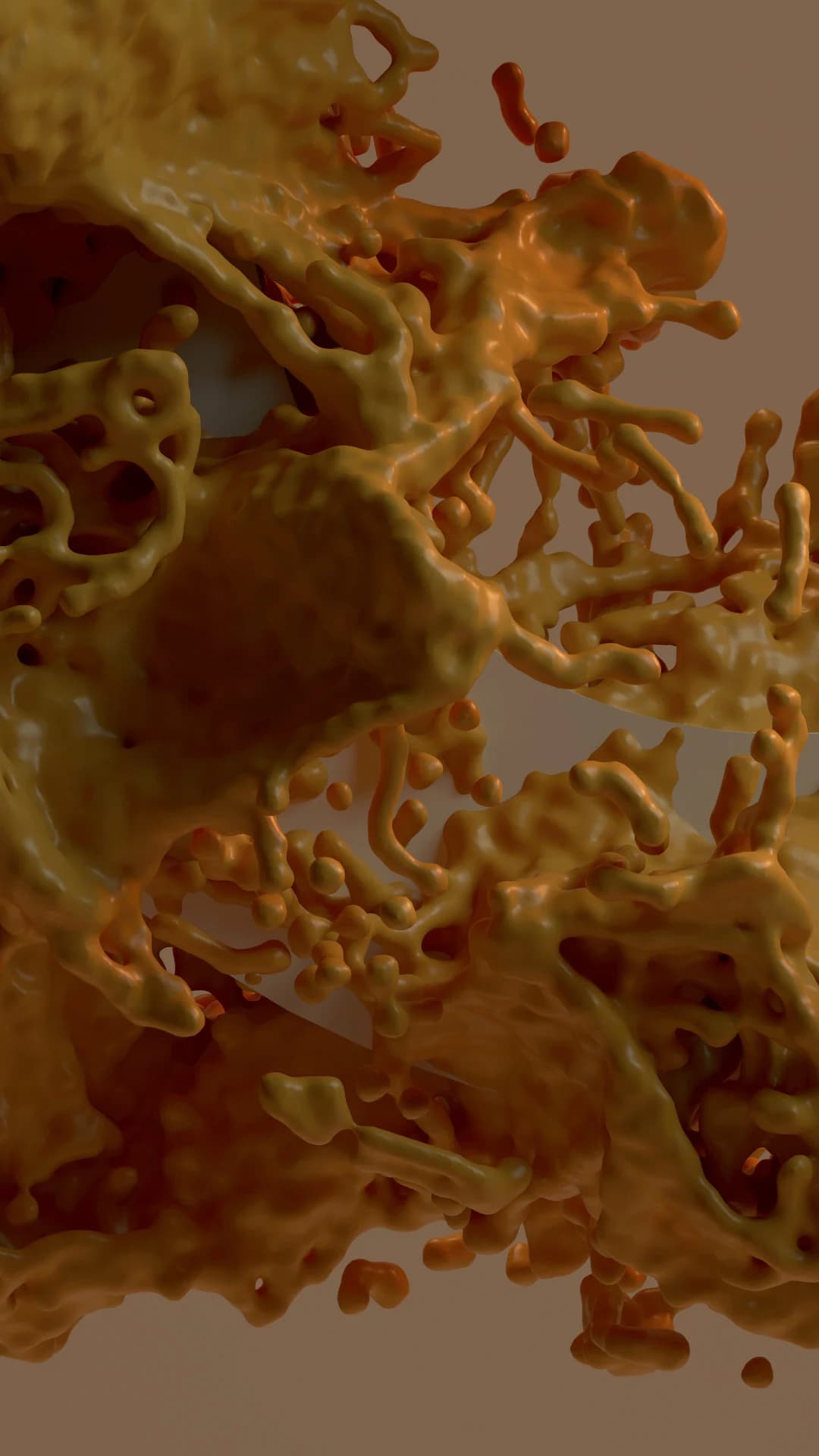
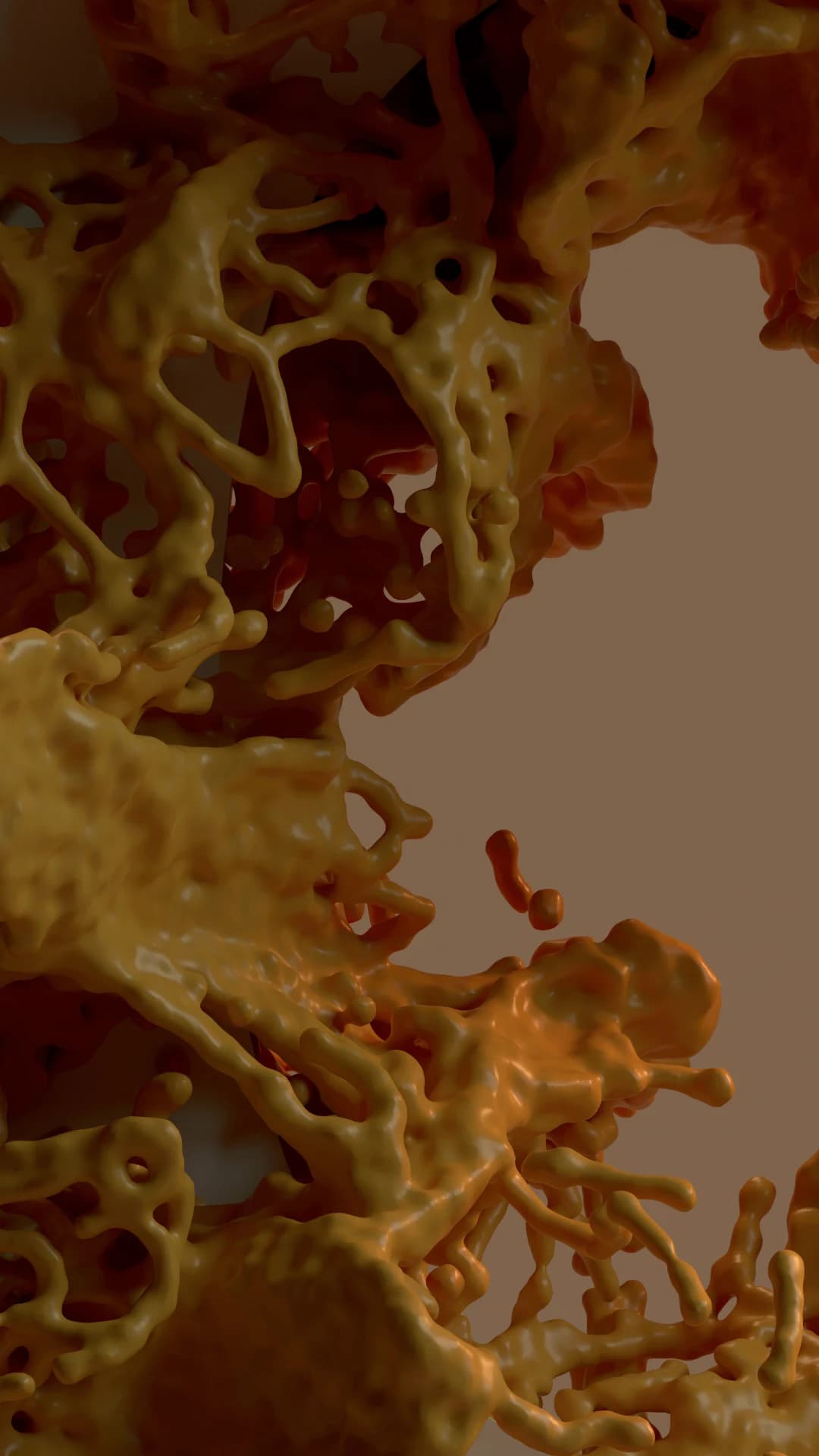
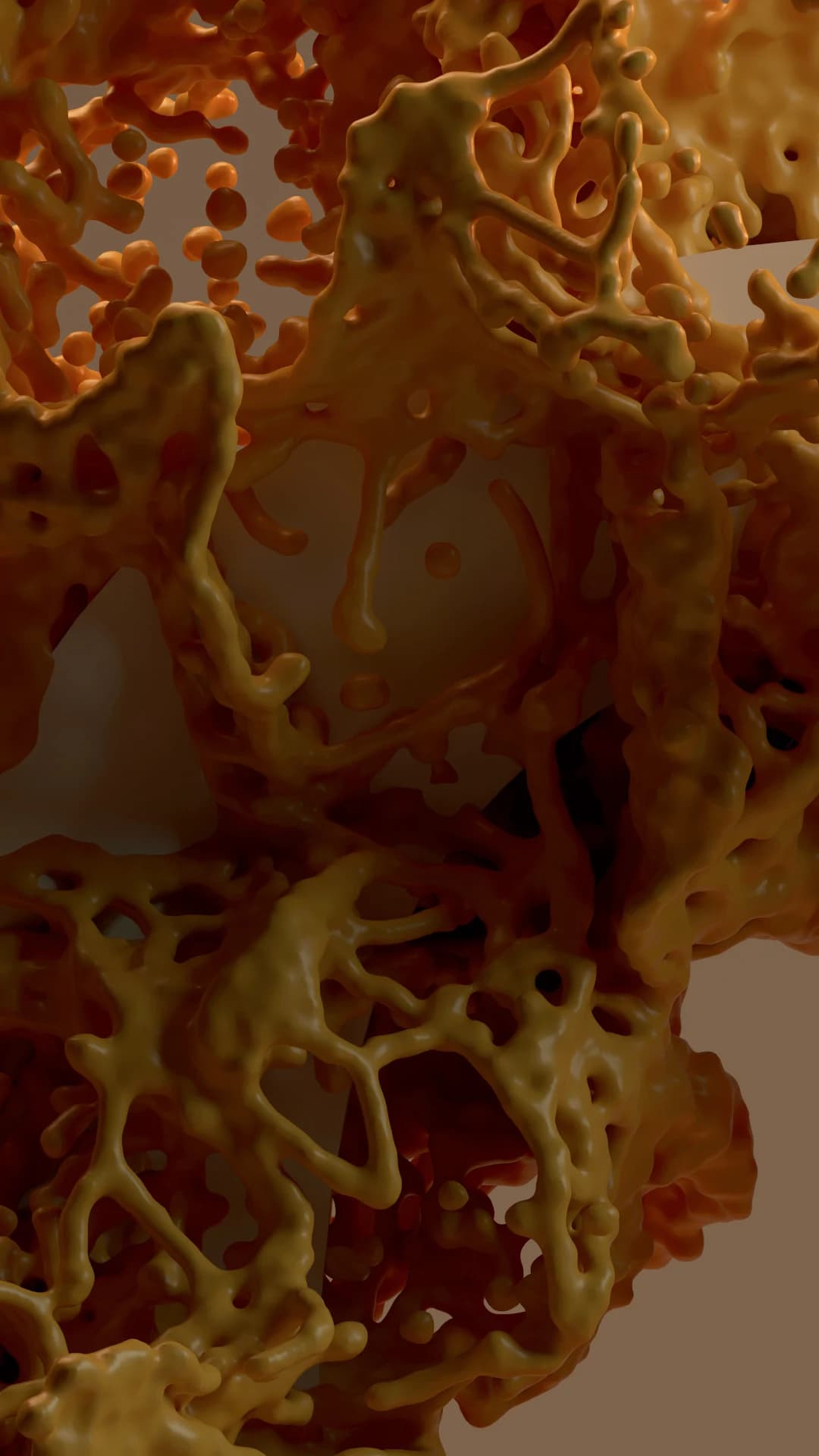
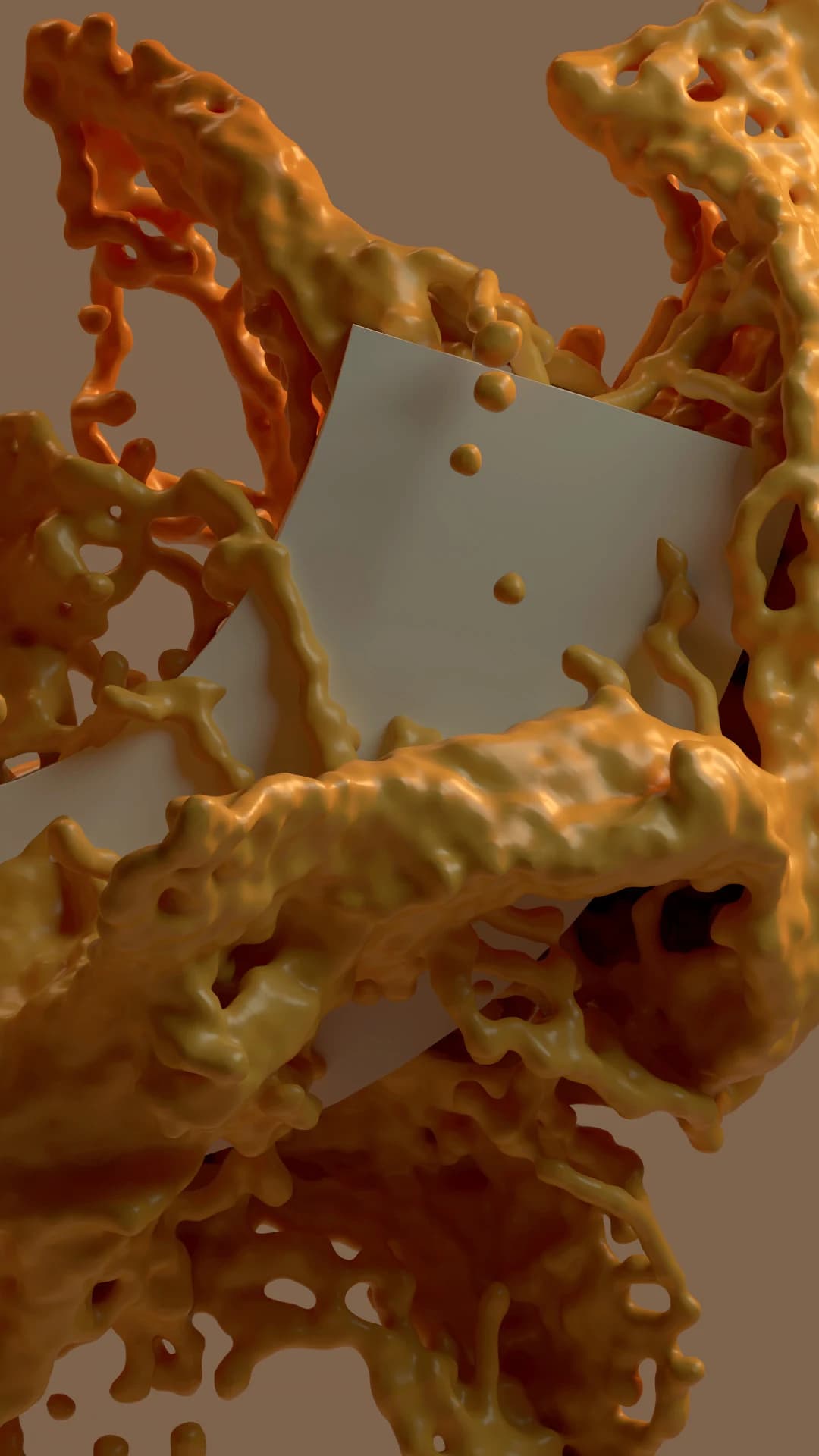
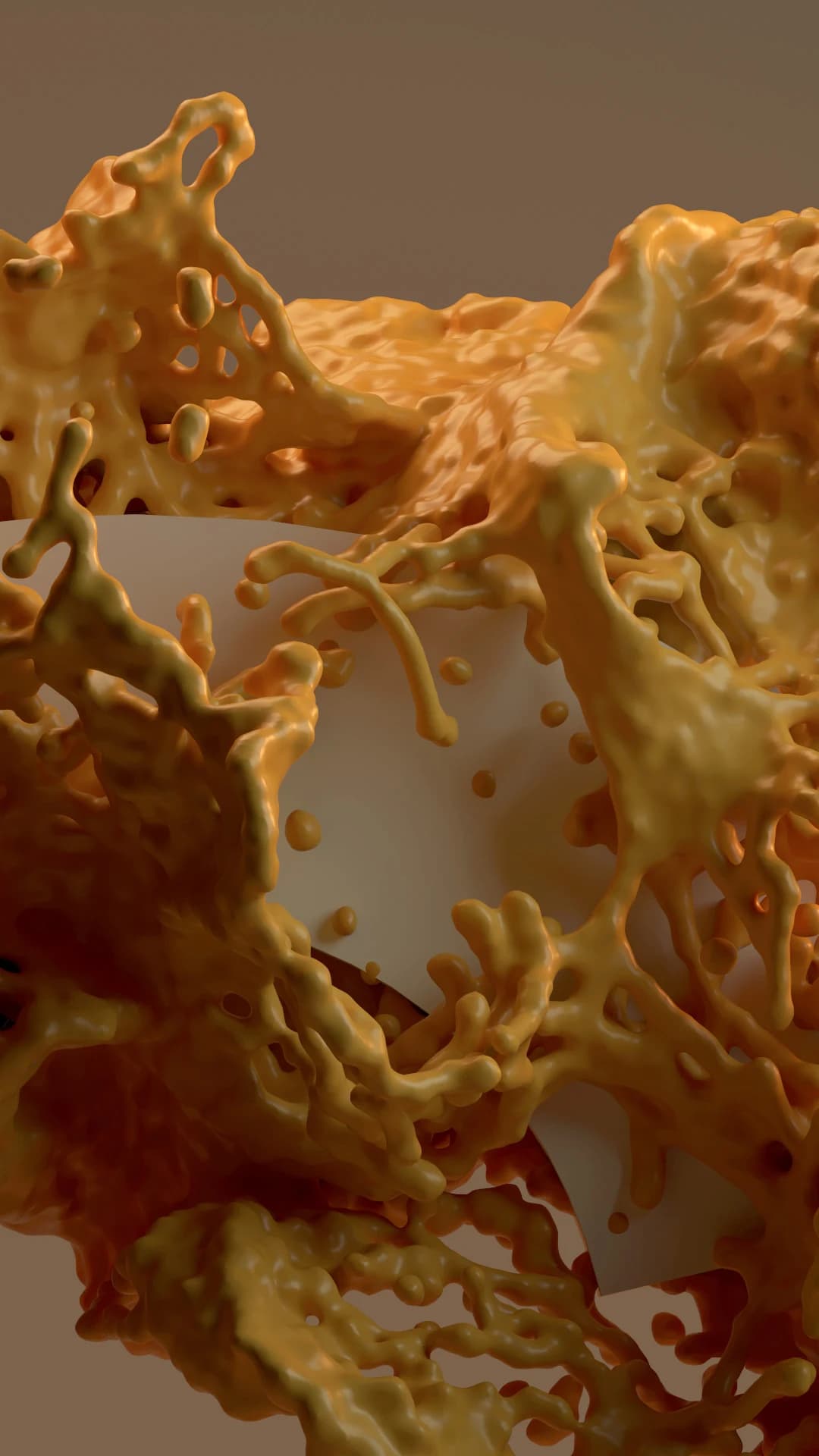
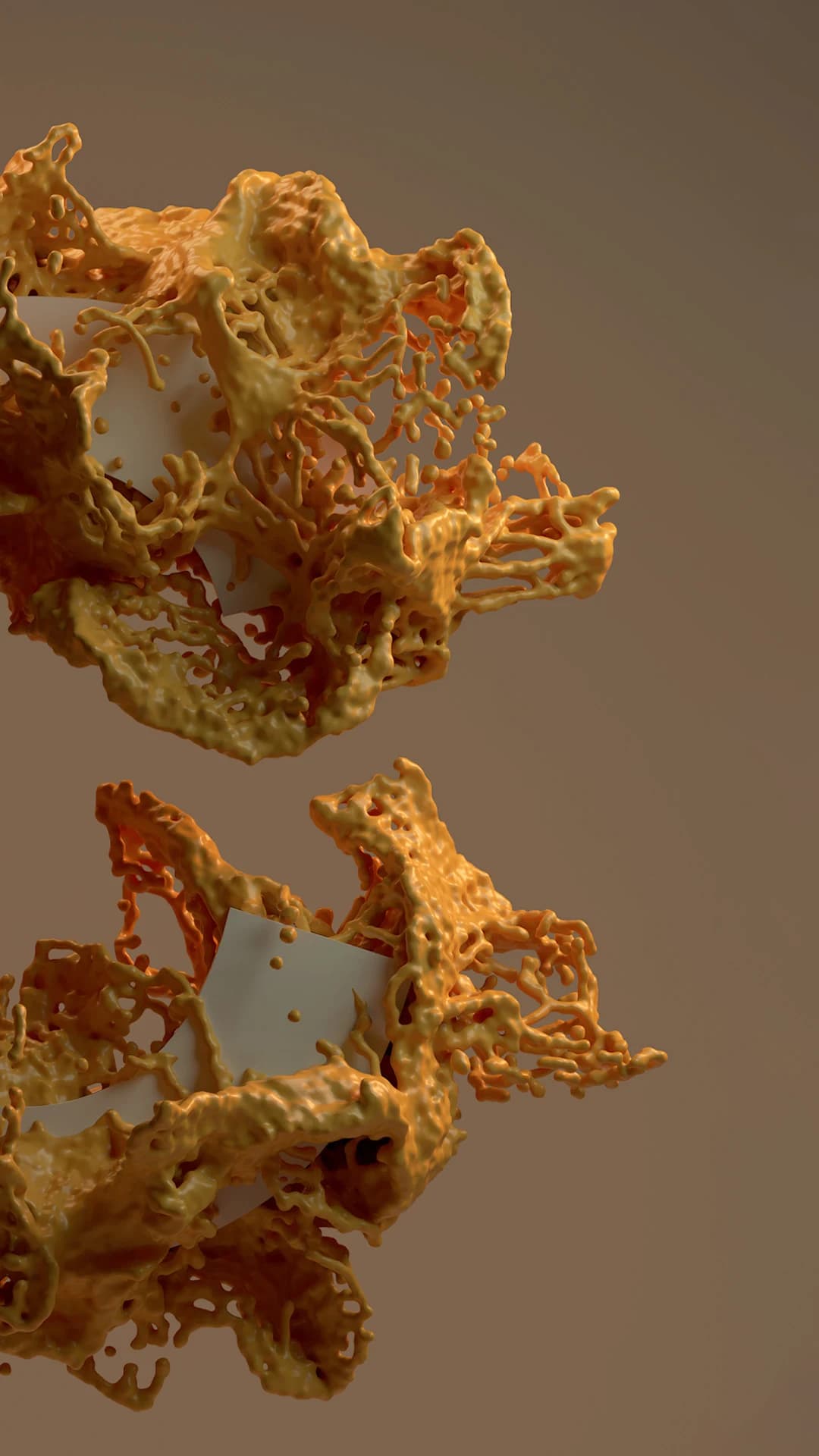
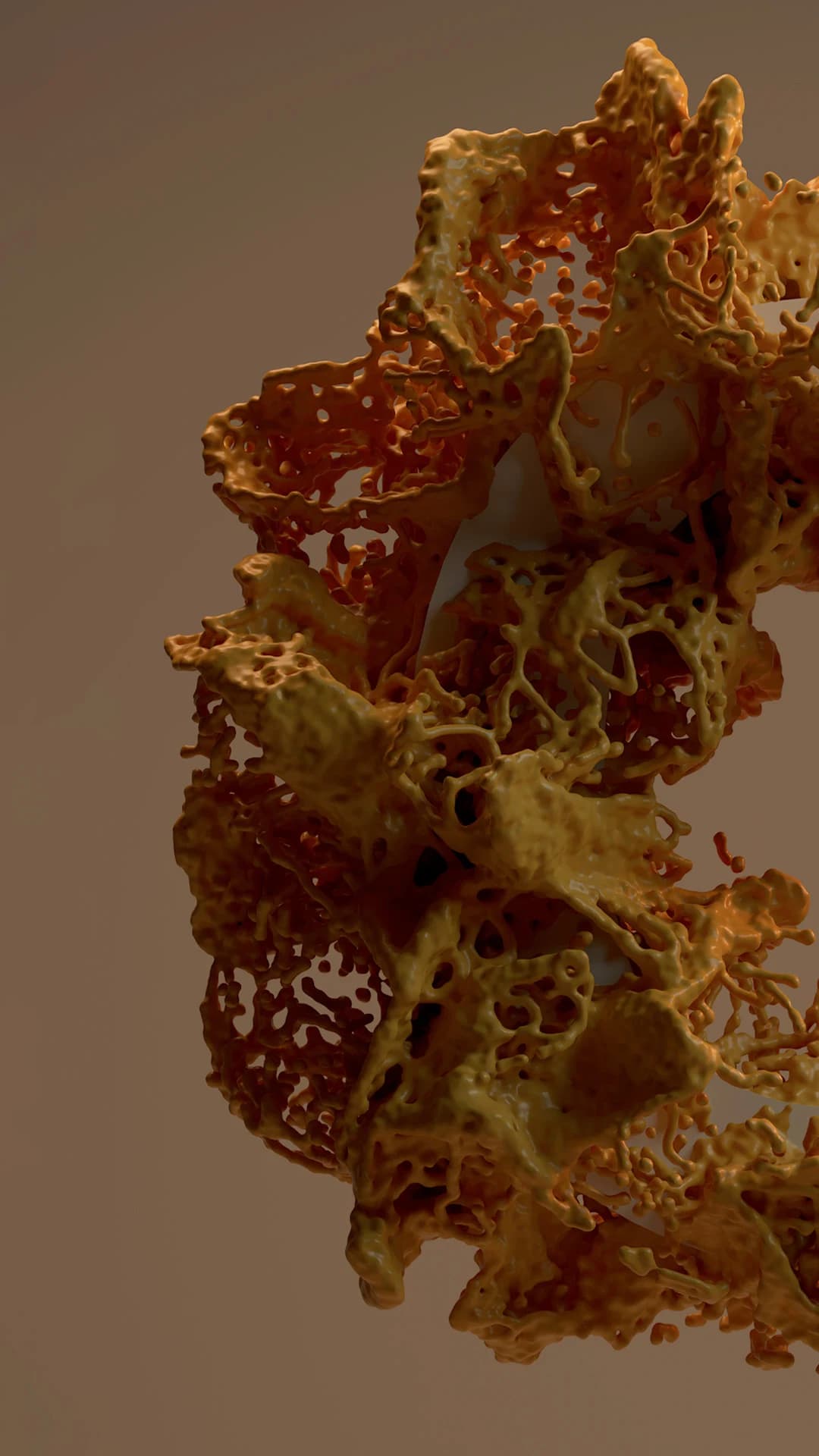
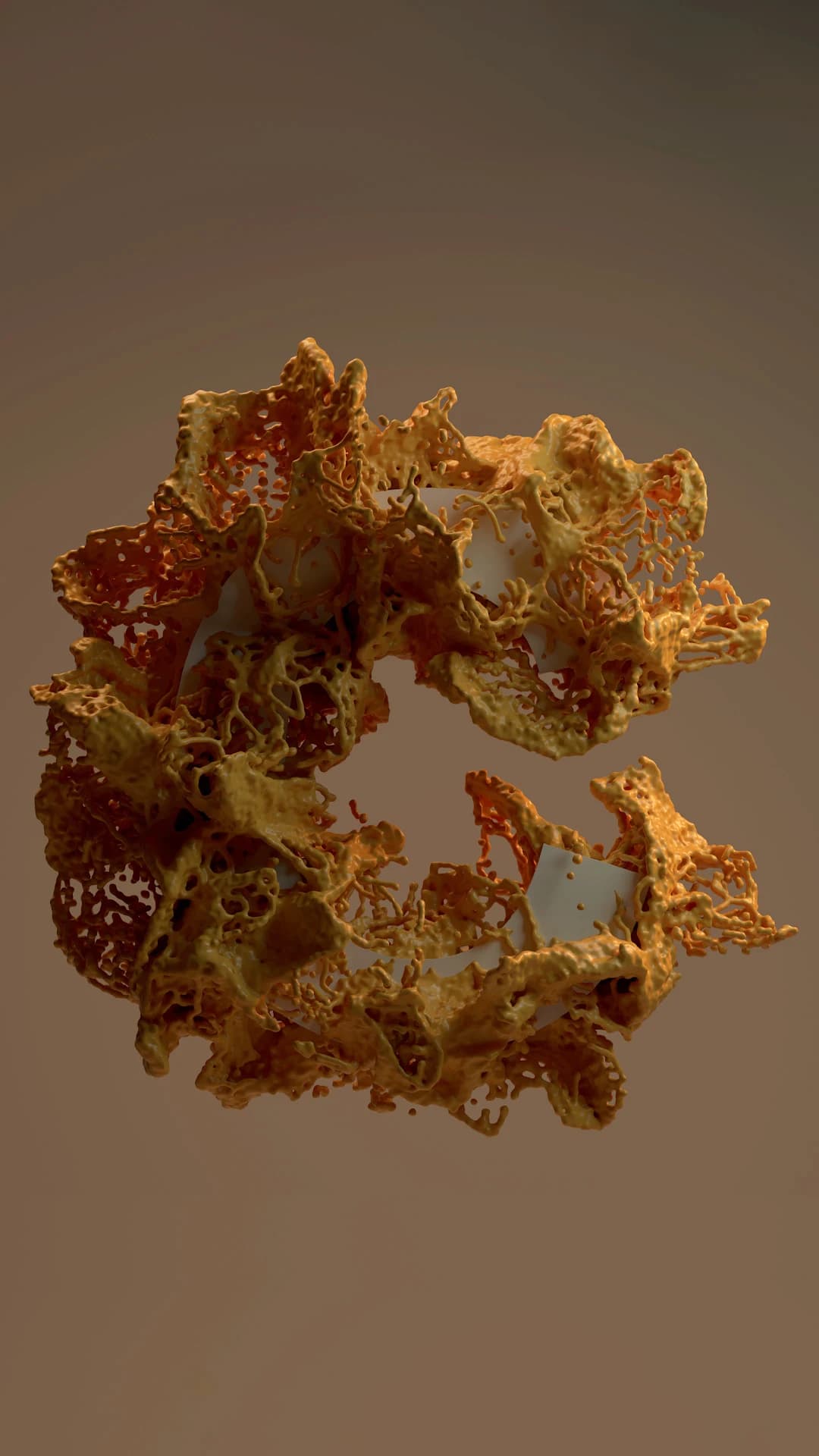
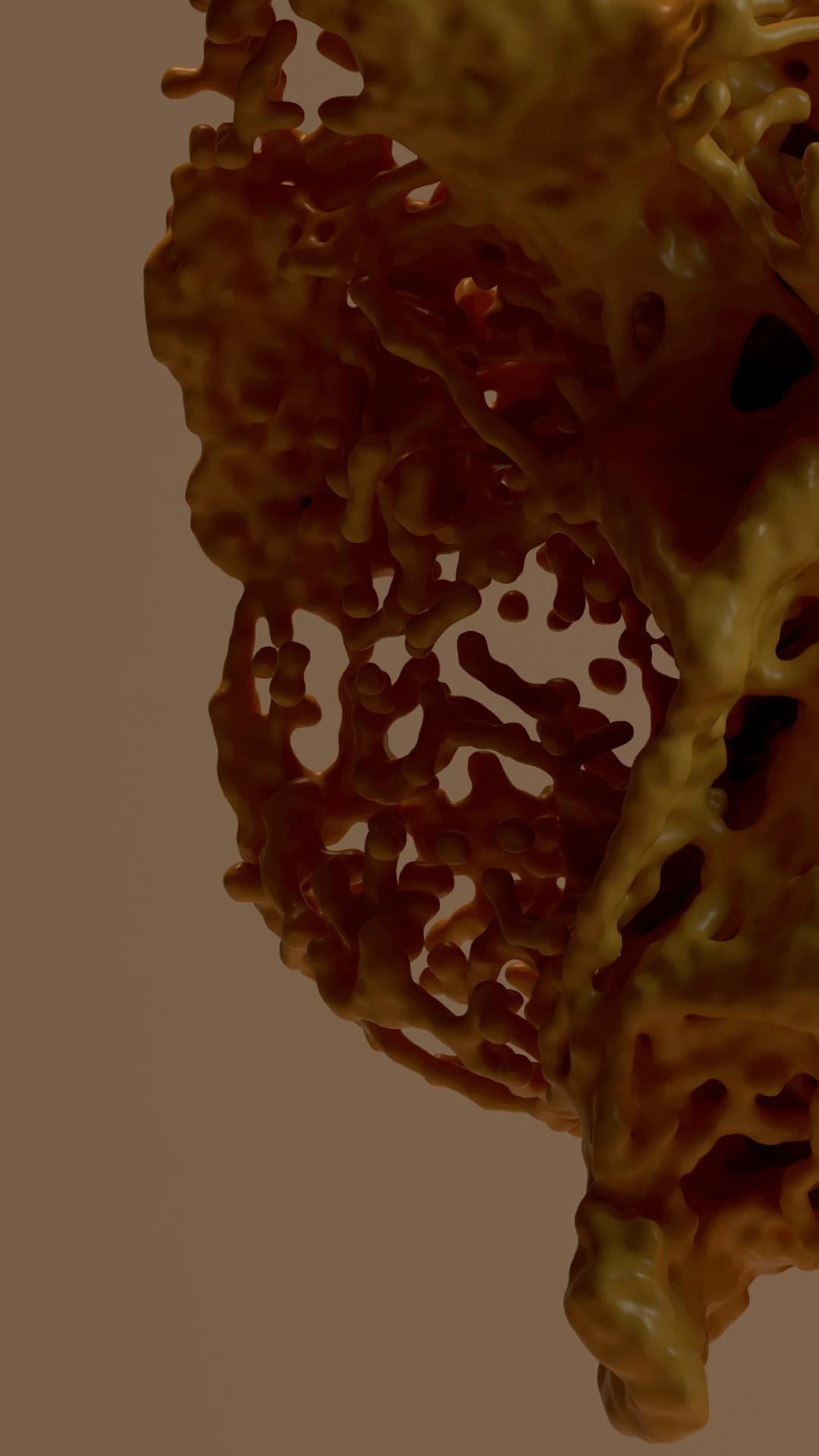
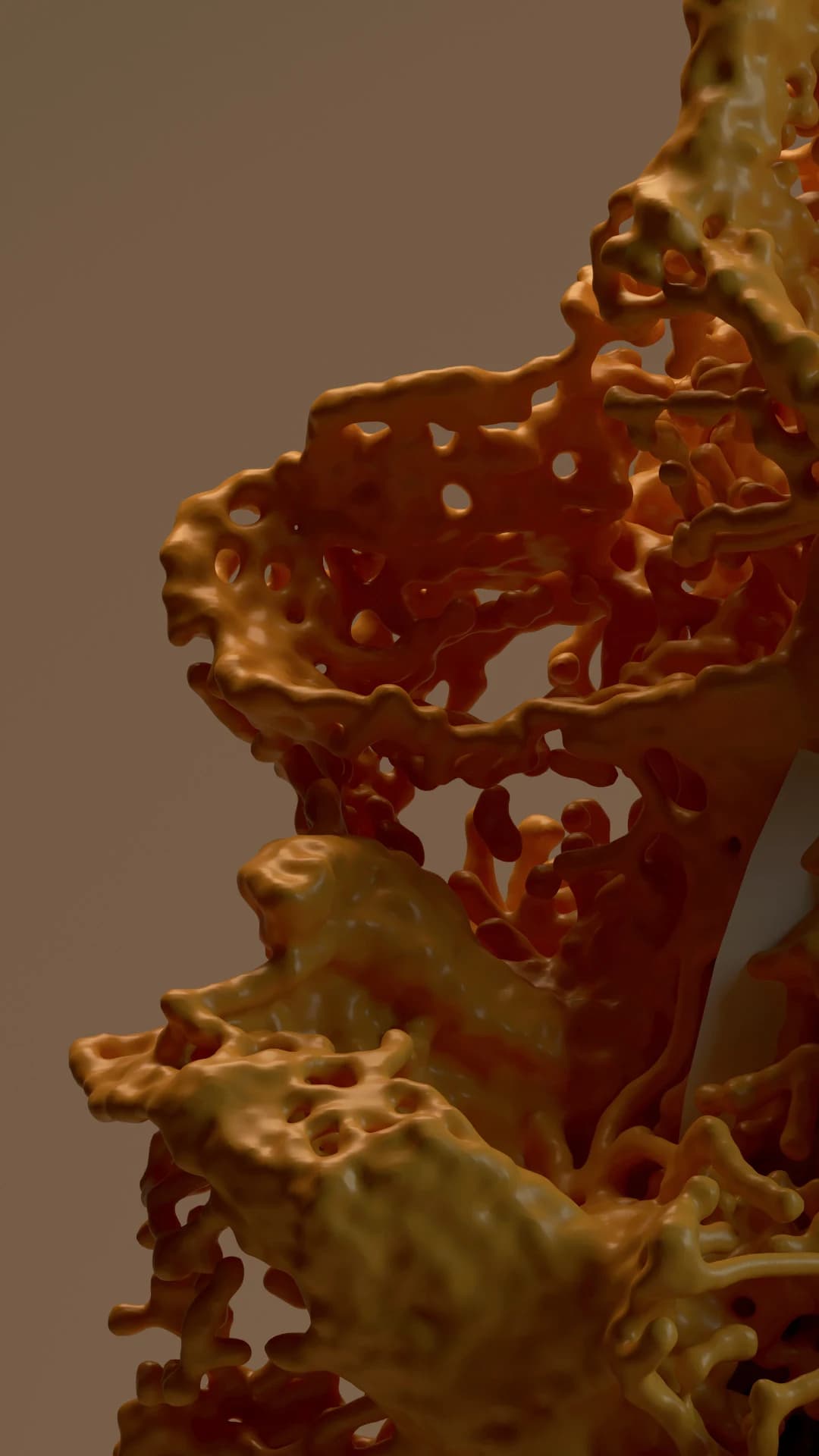
La letra como organismo. X-Particles convierte el contorno tipográfico en un emisor de partículas fluidas: las partículas se emiten desde la silueta, interactúan entre sí mediante simulación SPH y se fusionan en una isosuperficie continua. El resultado es una masa que crece desde la forma de la letra sin reproducirla — la mantiene como memoria estructural, no como silueta.
Cada glifo se construye como emisor en X-Particles. Las partículas fluidas (SPH) se emiten desde el perímetro del carácter y forman una isosuperficie de metaballs. El material — traslúcido con subsurface scattering — amplifica la sensación de masa biológica y la traslucidez orgánica. La paleta se limita a tonos cálidos sobre fondo neutro.
Construcción del contorno tipográfico → configuración del emisor SPH en X-Particles → simulación de fluido → generación de isosuperficie → asignación de material traslúcido (SSS) → iluminación de estudio → selección de encuadres y animación.